Trong thiết kế, ai cũng muốn tạo ra hiệu quả thân thiện với khách hàng. Lựa chọn dễ dàng và an toàn nhất mà 90% nhà thiết kế thường làm là : Chọn một phông chữ chữ thuộc họ hình tròn vì hình tròn mang lại cảm giác giác an toàn, vô hại.
Tuy nhiên, sự thiện thiện có 2 cấp độ: Trực quan và Phúc tạp. Nếu bạn áp dụng sai, thiết kế của bạn sẽ đánh mất toàn bộ sự nghiệp chuyên nghiệp!
Nhóm 1: Thân trực quan. Đây chính là con dao hai lưỡi
Công thức: Sử dụng các phông chữ có độ sắc nét, đầu tròn (đầu cuối) trịa, không có góc sắc, độ nét đều không tương phản (như Rounded Mplus 1c, VAG Rounded).
Khi nào dùng tốt? Vì nó có thể hiện sự an toàn, vô hại, nên nó cực kỳ hoàn hảo cho ngành hàng trẻ em (bỉm Pampers, dép Crocs), đồ gia dụng, hoặc siêu thị bình dân.
Cái bẫy (Rẻ tiền). Sự thay đổi lớn nhất của phông chữ tròn không có độ sâu. Nếu dùng cho ngành Tài chính, Công nghệ cao hay Xa xỉ, khách hàng sẽ thấy bạn giống một “tiệm tạp hóa”!
Nhóm 2: Thân thiện phức tạp. Bí quyết của Cao cấp đã được quyết định.
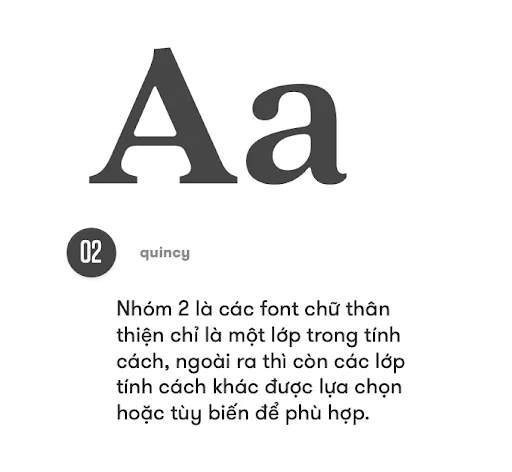
Vậy làm sao để thương hiệu gần gũi mà vẫn kéo tiền? Đừng bo tròn mọi thứ! Vui lòng cài đặt tính năng thân thiện:
Nét “Đong mực”: Mô phỏng lại mức độ lem của công nghệ in ấn thủ công cổ xưa để tạo cảm giác giác con người, mộc mạc.
Cấu trúc chữ tự nhiên. Sử dụng chữ cái thường xuyên thay vì trong phần cứng nhanh; use chữ ‘a’ và ‘g’ as 2 tầng cầu kỳ; hoặc nghiêng chữ viết mô phỏng.
Ứng dụng thực tế: Đúng & Sai. Khuyên dùng những kiểu chữ sau đây:
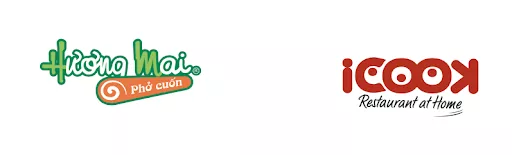
Những font chữ này hoàn hảo cho: Trẻ em, Gia dụng, Bình dân. Hình tròn tạo ra sự vô hại.
Case study 1: CAKE của VPBank
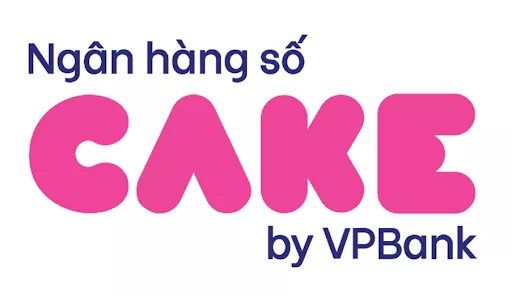
Sự đánh đổi để “Bắt mắt”
Cake là ngân hàng số tiền tới Gen Z. Họ làm thiện thiện “quá đà” bằng cách sử dụng font Sans Geometric bo tròn, độ sắc nét siêu dày, kerning (khoảng cách chữ) ép chặt và viết in hoa toàn bộ.
Logic: Cách làm này biến chữ thành một “mảng màu đồ họa” nổi bật. Cake đã chấp nhận hy sinh chiều sâu logic và sự lâu đời để đổi lấy sự nổi bật, tính truyền thông “bùng nổ” trên mạng. Nó hiệu quả với Gen Z, nhưng nếu một hệ thống truyền thông ngân hàng làm như vậy thì đó sẽ là thảm họa!
Case study 2: Sharp “Be Original”
Sự kiện gần gũi từ Lịch sử
Trong chiến dịch hướng tới người dùng, Sharp không gây hại cho font bo tròn mập. Họ sử dụng dòng Old Style Serif (font có chân cổ điển).
Logic: Dòng font này chứng minh lịch sử lâu đời và chất lượng ổn định. Cải thiện khả năng thực hiện tinh tế qua: chữ in thường tự nhiên, chữ nghiêng kiểu tay, và phần chân chữ (serif) được làm mềm. Kết quả: Vừa gần cá nhân hóa, vừa tỏa sáng cao cấp!
Góc Chuyên Gia: Giải thích sự thân thiện tinh tế
Đừng lướt qua. Hãy soi kính lúp vào từng “tế bào” của dòng chữ Old Style Serif.
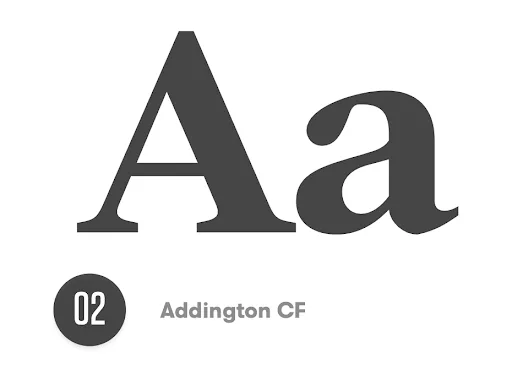
Bụng chữ 2 tầng: Gần gũi và cầu kỳ
Chân Serif và uốn cong: Mềm mại và phi cơ khí
- Mỏng chữ 2 tầng: Mang lại cảm giác quen thuộc của sách giáo khoa cổ, phức tạp và giảm tiền hơn.
- Chân Serif thông cong: Không được cắt sắc nét bằng máy móc, tạo cảm giác mộc mạc cho con người.
Kiểm tra trí nhớ: Ôn Tập Nhanh
Tại sao 90% nhà thiết kế chọn phông chữ bo tròn khi muốn thiết kế “thân thiện”?
Vì hình học bo tròn mang lại cảm giác giác an toàn, vô hại về mặt trực quan đối với não bộ.
Hai cấp độ của sự tiện lợi trong thiết kế chữ là gì?
Thân thiện Trực quan (Nhóm 1 – Cơ bản) và Thân thiện Phúc tạp (Nhóm 2 – Cao cấp).
Nhóm “Thân thiện trực tuyến” thường có cấu hình tạo nét đặc biệt?
Đầu nhọn (terminal) tròn trịa, không có góc nhọn, nét đều không có tốc độ tương phản.
Nhóm 1 (Thân thiện trực quan) ứng dụng TỐT NHẤT cho ngành hàng nào?
Ngành hàng trẻ em, đồ gia dụng, siêu thị bình dân hoặc các chiến dịch Sale/Khuyến mãi đại chúng.
Lỗi lớn nhất (Cái bẫy) khi sử dụng phông chữ tròn là gì?
Làm mất đi chiều sâu, tạo ra thương hiệu và thiết kế trông “rẻ tiền”, thiếu sự chắc chắn và tin cậy.
Ngành Tài chính chính / Bất kỳ sản phẩm nào sử dụng phông chữ bo tròn sẽ gây ra hậu quả tâm lý gì?
Trông giống như một “tiệm tạp hóa” hoặc “nhà trẻ”, tạo khách hàng e không sành giao phó tài sản lớn.
Ngân hàng Cake đã sử dụng kết hợp thuật toán nào để nổi bật với Gen Z?
Sử dụng phông chữ bo tròn + độ nét cao + kerning (khoảng cách) ép chặt + viết trong toàn bộ bộ.
Cake phải “đổi” điều chỉnh gì khi sử dụng phong cách thiết kế này?
Hi sinh sự lâu đời, chững chạc và chiều sâu logic để đổi lấy sự bắt mắt, nặng bom truyền thông trên trực tuyến.
Để thương hiệu gần gũi nhưng vẫn CAO CẤP, ta nên áp dụng nhóm thân thiện nào?
Thân thiện Phúc tập (Nhóm 2).
Kỹ thuật “Inktrap” (Đong mực) tạo ra cảm giác giác độ thiện bằng cách nào?
Mô phỏng mức độ công nghệ trong thủ công cổ xưa, mang lại vẻ đẹp nguyên sơ, mộc mạc của con người.
Thương hiệu Sharp trong chiến dịch “Be Original” đã chọn phông chữ dòng nào?
Dòng Old Style Serif (Font có chân cổ điển).
Cấu hình chữ ‘a’ và ‘g’ dạng 2 tầng mang lại cảm xúc gì?
Vì sao dùng “chữ in thường” (chữ thường) lại thân thiện hơn “chữ in hoa”?
Chữ in hoa tạo thành khối vuông vức thể hiện kỷ luật, lý trí. Chữ in bấm nút cảm xúc, đời thường.
Công thức tóm tắt cho “Thân thiện cấp cao” là gì?
Font có chân cổ điển
Chữ in thường
Hướng nghiêng tự nhiên
Nét nhạt mực.
Ranh giới mong manh…Giữa sự “Thân thiện cao cấp” và “Bình dân rẻ tiền” đôi khi chỉ cách nhau ở một mức độ rõ ràng hay độ công của chữ ‘a’. Đừng để thiết kế của bạn mất điểm trong đối tác!